11 خط مجاني مستوحى من هاري بوتر
نشرت: 2019-10-28في بعض الأحيان يحتاج المشروع إلى القليل من السحر الإضافي. لهذا السبب قمنا بتجميع مجموعة من أفضل الخطوط المجانية المستوحاة من هاري بوتر والتي يمكن أن نجدها. من الأناقة والساحرة إلى الخربشة والمخربشة ، ستعمل خطوط هاري بوتر هذه على رفع تصميمك أكثر مما لو ألقيت wingardium leviosa .
1. عالم السحر
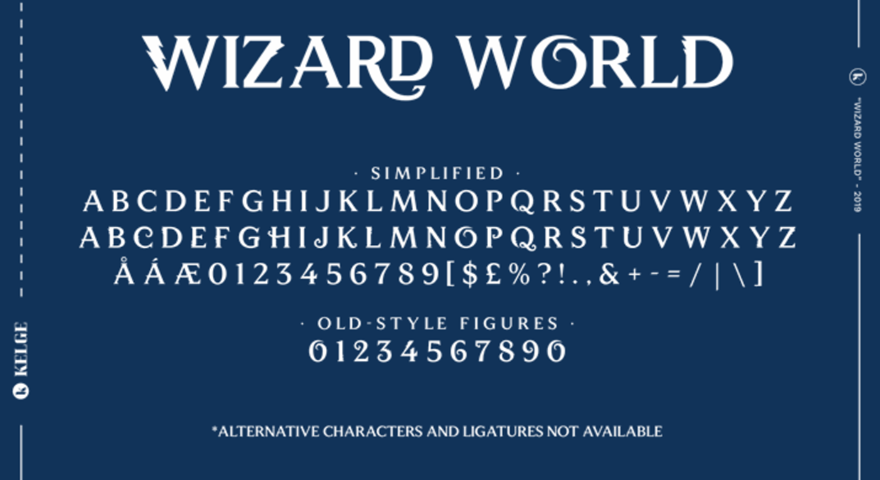
بدء القائمة قوية ، Wizard World هو ما يريده الكثير من الناس في خط Harry Potter. إنه أنيق ومقروء ومصمم للعناوين والأقسام. يتضمن التنزيل أشكالًا قديمة الطراز تزدهر أكثر ونسخة مبسطة يمكنك مزجها بأسلوب أقل بهرجة. إذا كنت في حاجة إلى خط Harry Potter تقليدي إلى حد ما ، فهذا ليس مكانًا سيئًا للبدء.
2. الرومانسية القاتلة بريما
قد لا يحتاج مشروعك إلى شيء مليء على وجه التحديد بسحر هاري بوتر ، ولكن بدلاً من ذلك ، تريده أن يستحضر فقط إحساس العالم السحري ، قد تكون Romance Fatal Prima هي ما تبحث عنه. مع إحساس مكتوب بخط اليد مع تقنين وتتبع غريب الأطوار وجريء إلى حد ما ، فإن هذا الخط ليس خيارك المعتاد. متاح مجانًا للاستخدام الشخصي ، ولكن مع الترخيص التجاري ، لديك مجموعة كاملة من الشخصيات لأداء أي سحر تريده.
3. بارسيلتونجو
ليست متعرجة وزلقًا تمامًا كما قد يتوقع المرء من لغة الثعبان التي تحمل اسمها ، ومع ذلك توفر Parseltongue الشعور الصحيح لأي شخص يرغب في إضافة القليل من الإثارة إلى عملهم. حواف ولهجات حادة ، ومنحنيات كافية لاستحضار الاسم نفسه. التباعد مبهج ، على الرغم من وجود العديد من الفروع. يتيح ذلك للسيناريو أن يبدو أنيقًا وساحرًا ، بينما من الواضح أنه لا يزال جزءًا من عالم Muggle الدنيوي.
4. Xefora
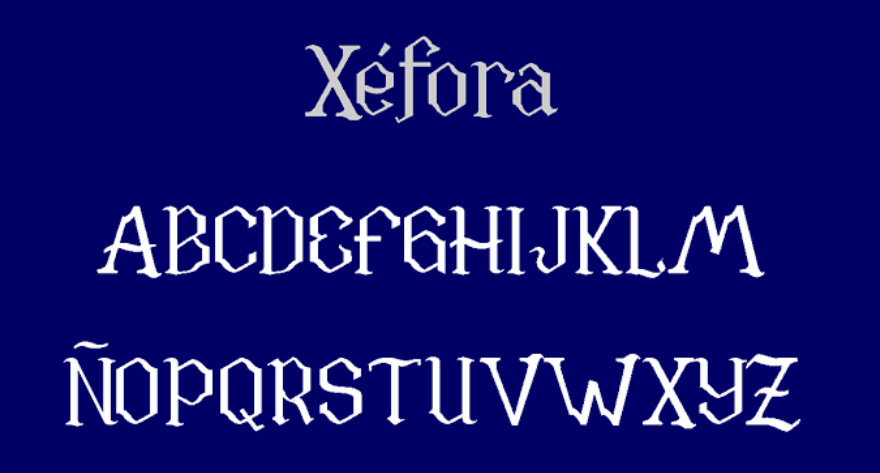
Xefora هو اسم غريب لخط غريب. وواحد تريد إضافته إلى مكتبتك على الفور. مجاني للاستخدام الشخصي ، ويتطلب تبرعًا للمشاريع التجارية ، يأتي الخط بأحرف كبيرة وصغيرة وسيكون موجودًا في المنزل مباشرةً في كتاب إملائي كما هو الحال في نشرة حفلة أو دعوة زفاف. بغض النظر عن استخدامك النهائي ، فإن Xefora يستحق التنزيل لأي شخص يبحث عن خط Harry Potter أو خطين.
أنا أحب الزنجبيل
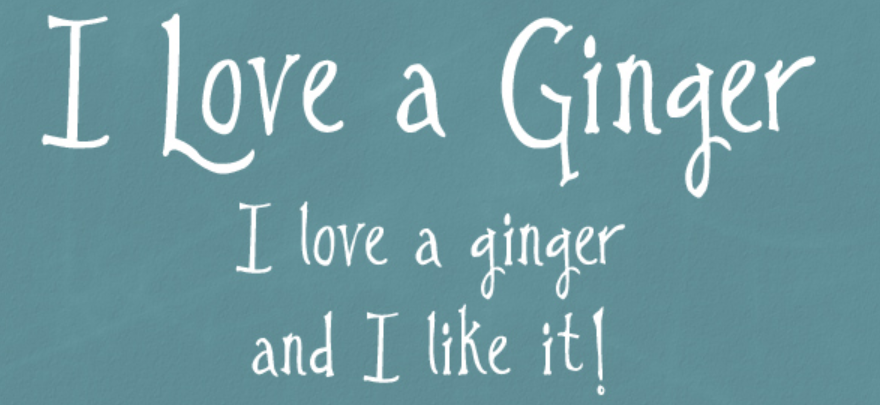
ربما يكون الخط المفضل لدينا في القائمة بسبب الاسم ، أنا أحب الزنجبيل مبهج ويستحق الوقوع في حبه في حد ذاته. مثل هيرميون ورون أو هاري وجيني ، بعض الأشياء تسير معًا. ولا تختلف أحرف هذا الخط وصوره الرسومية. سوف يقومون بإضفاء الحيوية على تصميماتك ، مما يضيف إحساسًا غريبًا وشعورًا مكتوبًا بخط اليد ، بالإضافة إلى إضفاء القليل من الدفء على المشروع بأكمله. بمجرد النظر إلى هذا الخط الدافئ والجذاب ، كنا نلتف في Burrow مع عائلة الزنجبيل المفضلة لدينا.
أنا لست ساحرًا
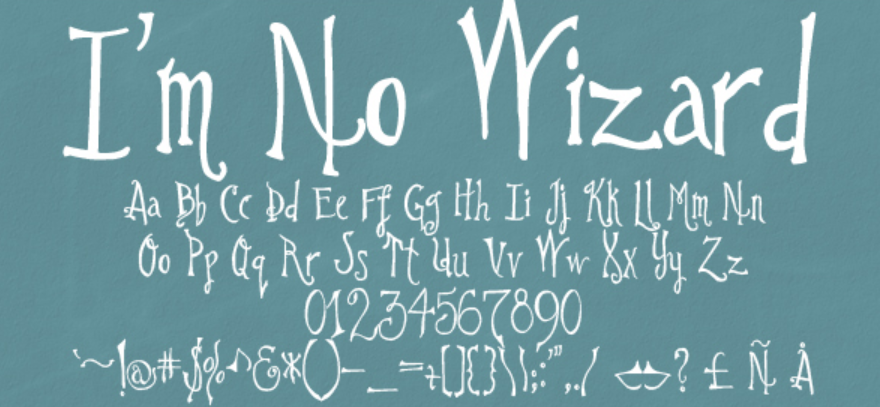
I'm No Wizard هو من نفس المصمم مثل I Love a Ginger. الخطان متشابهان ، لكن هذا الخط يتمتع بجودة تشبه الإملاء. بدلاً من النص الدافئ والودي ، لدينا خط مجعد في بعض الأماكن ، وحاد في أماكن أخرى ، وغير متماثل مع تقنينه وتتبعه لإبقاء العينين منشغلتين وتنشيط الخيال. أكثر تقليدية فيما يتعلق بخطوط هاري بوتر ، أنا لا معالج موجود في الجزء العلوي من قوائمنا للخطوط التي تجعلنا نرغب في التقاط عصا والبدء في التصميم.
هاري بوتر و Dingbats
Dingbats (والأجنحة) هي الخطوط التي تستخدم الصور كأحرف بدلاً من الأحرف والأرقام والرموز العادية. تُستخدم هذه الصور كخطوط لأغراض القياس ، مع إبقاء الصورة أو الشعار واضحًا بجميع الأحجام. هذا ما هو هذا الخط. إذا كنت بحاجة إلى شعار أو صورة سريعة لشيء ما من Potterverse ، فراجع dingbats.
باري هوتتر
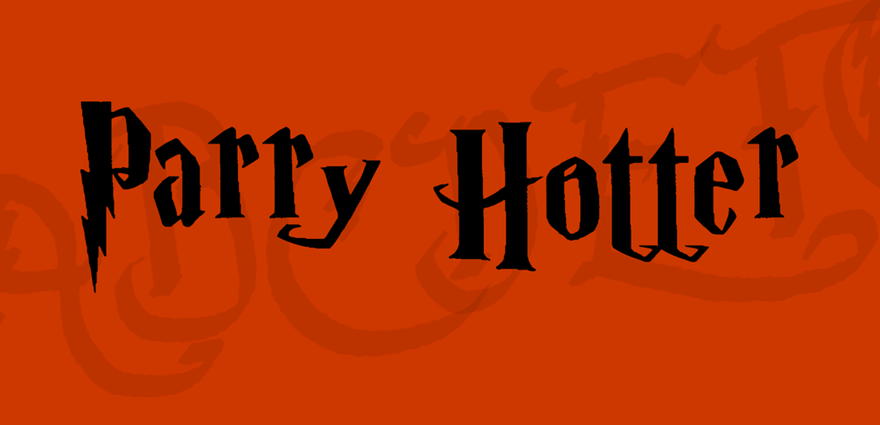
ربما يكون أكثر خطوط هاري بوتر تقليدية في قائمتنا ، تم إصدار Parry Hotter كبرنامج تجريبي لمتعة الجميع. بتقليد خط نشر فيلم HP بشكل لا يصدق ، فإن Parry Hotter لديه الكثير من أجله. ومع ذلك ، فإننا نقدم النصيحة لاستخدامها في العناوين وهذا النوع من الأشياء فقط. عند استخدام هذا الخط على عدة أسطر وجمل وفقرات ، يكون من الصعب جدًا قراءته.
مدرسة السحر
ما هي مجموعة الخطوط حول سلسلة من الكتب التي تحدث في مدرسة السحر والتي ستكتمل بدون خط بعنوان Magic School؟ بالتأكيد ليس هذا. ربما تكون Magic School هي ما تفكر فيه عندما تسمع عبارة Harry Potter font ، وهذا وحده يجعل الأمر يستحق المراجعة. ما يجعله يستحق التنزيل هو أنه ليس من الناحية الفنية مجرد خط واحد ، بل خطان. يمكنك الحصول على نص أكثر أناقة وأسلوب القرون الوسطى باستخدام خط Magic School One ، ويمنحك Magic School Two شخصيات ذات تصميم سحري أكثر ، مع إضاءة ولهجات أكثر وضوحًا وتزدهر على الشخصيات.
Kingthings Willowless
Kingthings Willowless جميلة ويصعب قولها. مزينة بالنجوم والدوامات والازدهار الذي سيجلب الفرح للمشاهدين بالتأكيد ، Kingthings Willowless هو مجرد خط جميل. مرة أخرى ، يبدأ هذا في الظهور بشكل غير منظم نظرًا لاستخدامه في الكثير من المساحات ، لذا اجعل عملك قصيرًا ولطيفًا ، وستجذب جمهورك.
حيوانات رائعة
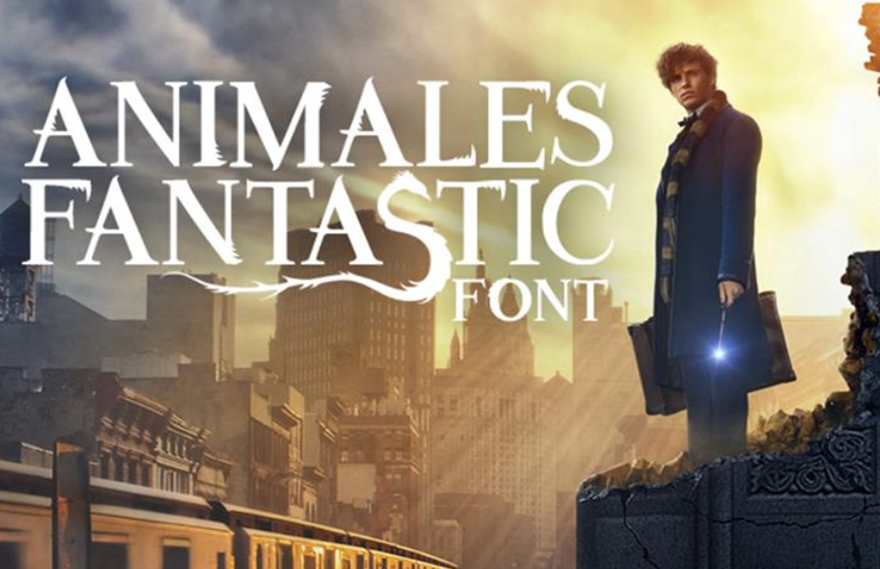
من الناحية الفنية ، تم تصميم خط Animales Fantastic لمحاكاة الجانب الأمريكي من Potterverse. مع الأنياب والفراء وذيول الانزلاق (أو هل هذا سليذرين؟) ، فإن الحروف الرسومية في هذه المجموعة رائعة بما يكفي لكسب الخط اسمه. عادةً ما يكون خطًا عاديًا وعاديًا ، ويزدهر الديكور على بعض الأحرف (ولكن ليس كلها) مما يجعل هذا الخط أكثر دقة من البعض ، ولكنه لا يزال ينضح بالسحر الذي تبحث عنه.
استنتاج
يمكن للسحرة والسحرة أن يتفقوا جميعًا على الطبيعة السحرية لهذه الخطوط. من السخيفة إلى الأنيقة ، فإن خطوط Harry Potter التي قمنا بتجميعها هنا ستجعل أي من تصميماتك تنبض بالحياة. خذ بضع دقائق لتنزيل مفضلاتك ، ونحن على يقين من أن الإلهام سيضرب قبل أن تعرفه.